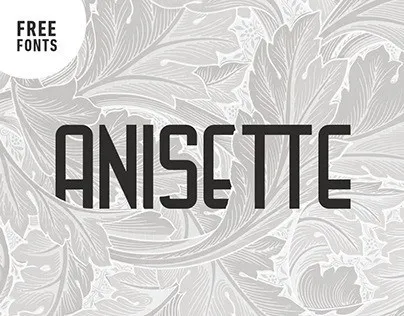
Anisette Sans Serif Font – Download Grátis
Anisette Sans Serif é uma fonte clara e divertida projetada por Adrià Martí para a plataforma 99designs. Esta fonte singular e diferente traz ao seu design um toque de diversão, tornando-a perfeita para qualquer projeto que você deseje dar aquele toque especial. Com seis pesos da tinta (grosa até negra), incluindo letras maiúsculas e minúsculas, números e símbolos, ela está disponível como uma fonte de tipo livre baseada em uma reinterpretação de um modelo tipográfico estilizado que se popularizou no século XX. Este modelo é geralmente considerado modernista e tem uma conexão especial com a cultura espanhola-francês, frequentemente usado na indústria. Os benefícios adicionais de Anisette incluem seu catálogo tipográfico completo que contém o alfabeto e cada letra possuindo seu próprio caderno de letras do alfabeto no verso. Além disso, a fonte vem em forma de cartão postais que podem ser separados para uso comercial. Essa fonte singular é perfeita para designers que procuram uma maneira única de dar vida à sua criação visual, oferecendo estilo único e diversão com um toque moderno e sofisticado.